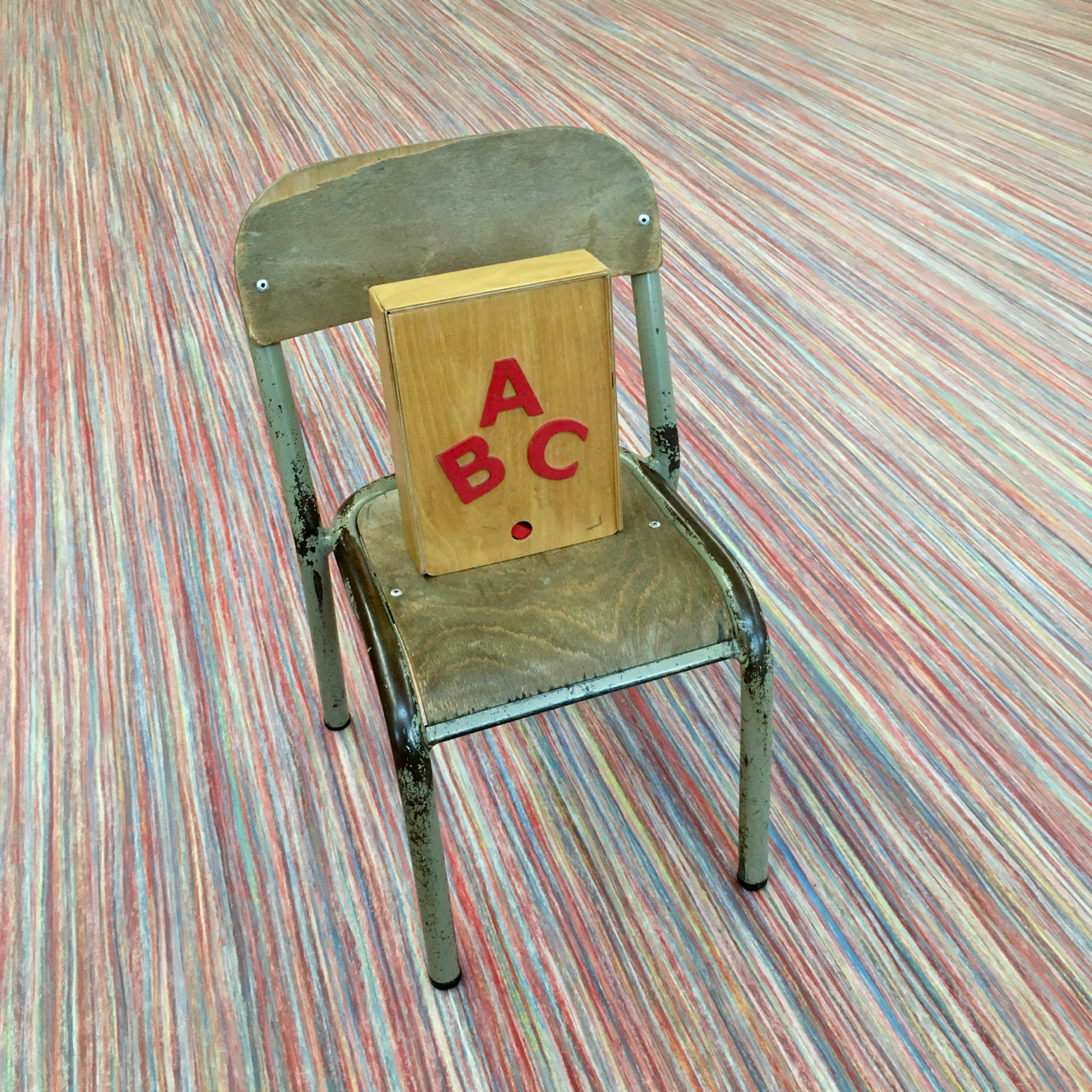
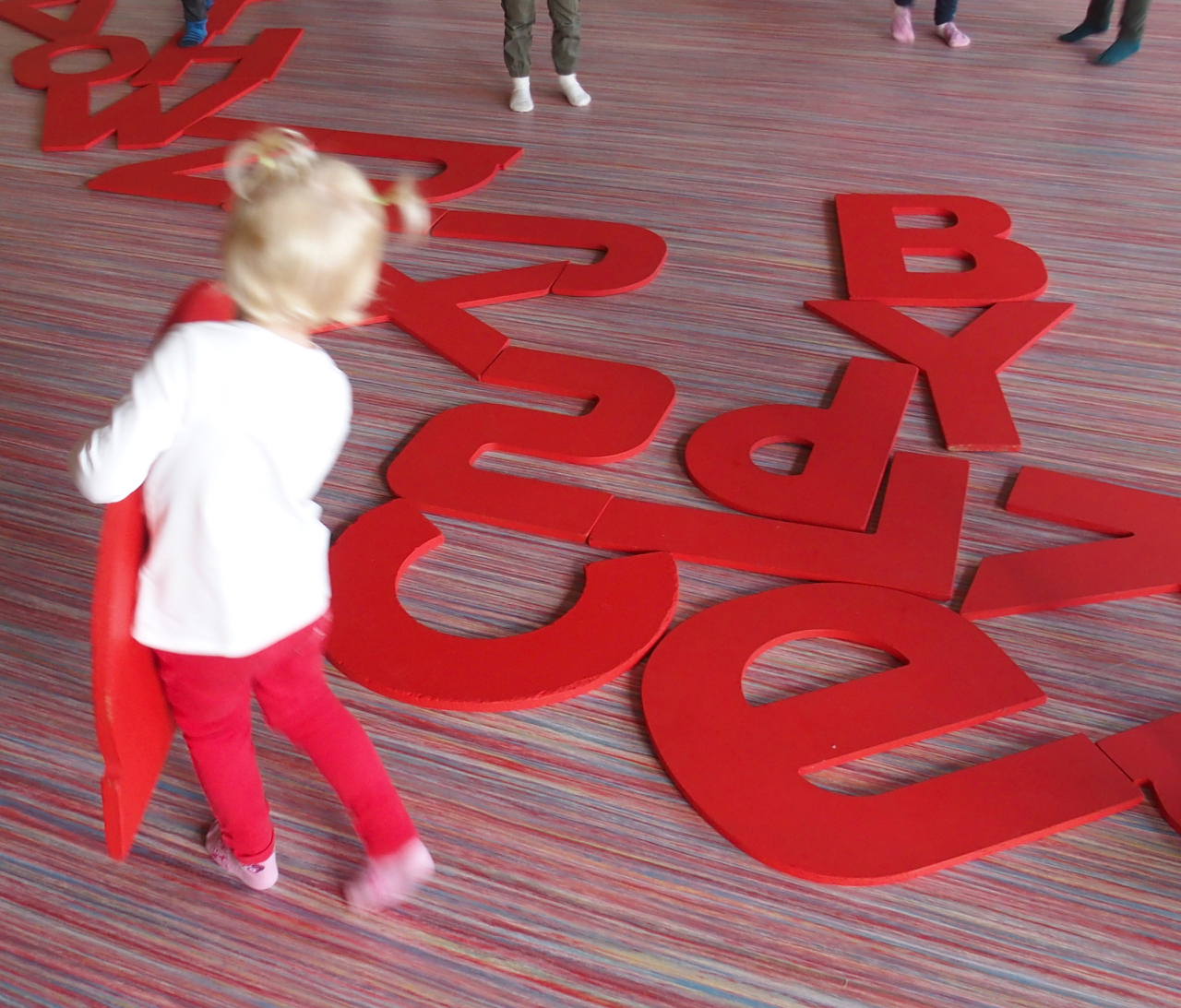
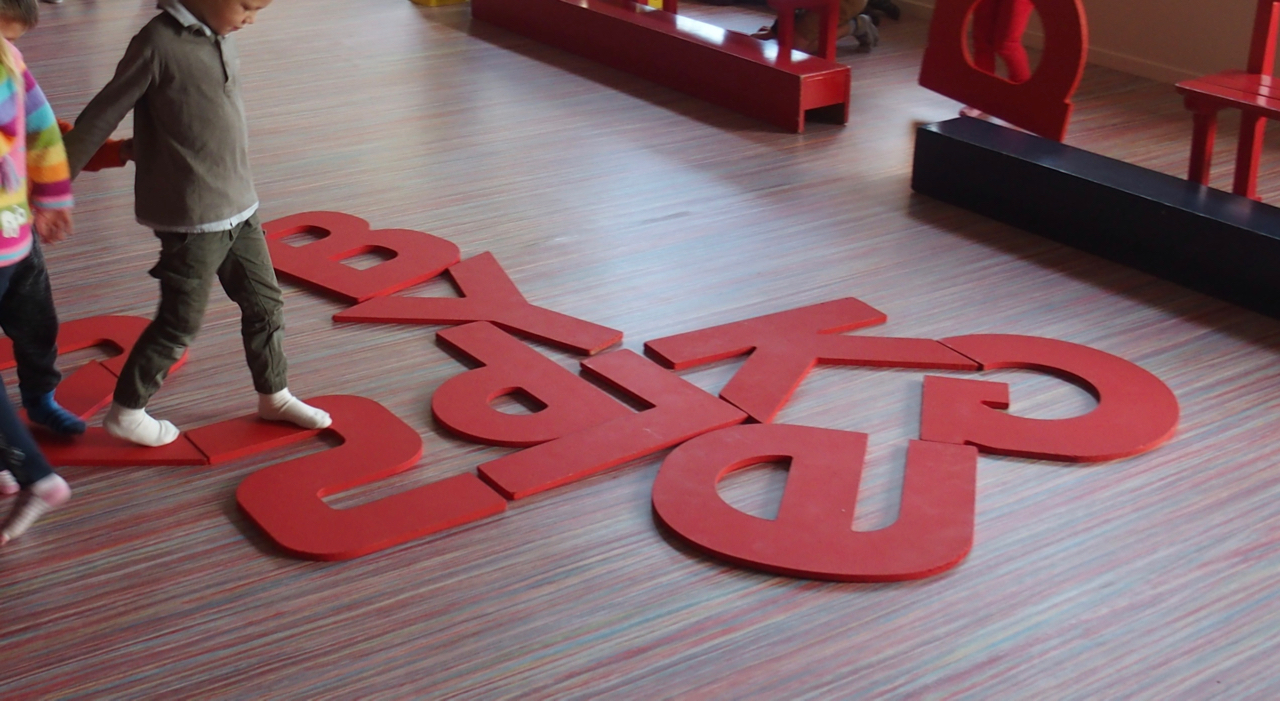
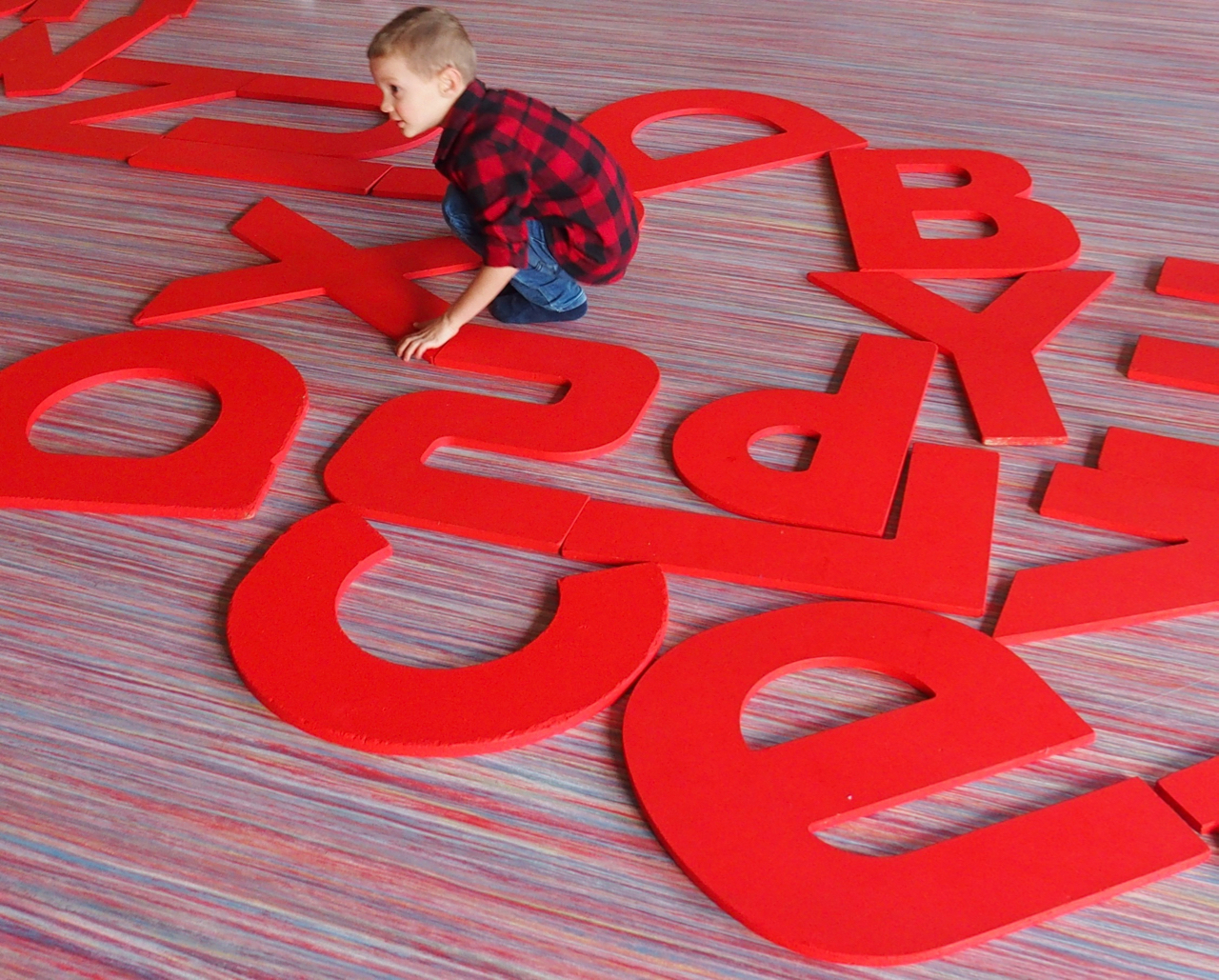
Quand les lettres sont encore de grandes inconnues, anonymes, ou presque.
On joue avec. Avec celles que l’on connait, reconnait, celles du prénom.
On les bouge, prend la mesure de leurs formes, par le corps, les mains. On les cherche, dans le troupeau rouge, on les porte. On s’en sert de porte, on passe sous les ponts, des n, des m… On fait des chemins, d’un mot, on marche dessus, le pied attentif, avant de se poser, jaugeant la lettre, pour, si possible dire son nom, avant de la piétiner. Si on ne la connait pas, d’autres l’on dans leur prénom et la connaisse.
Et puis on communie, en choeur, dans la chanson de l’alphabet.
Plaçant les 26 amis, ordonnés, dans la mémoire procédurale, durable, la base de tout ce qui va suivre.
L’apprentissage de l’écrit.
Un code. Naturalisé.
26 lettres, tout au long d’une vie, ici.